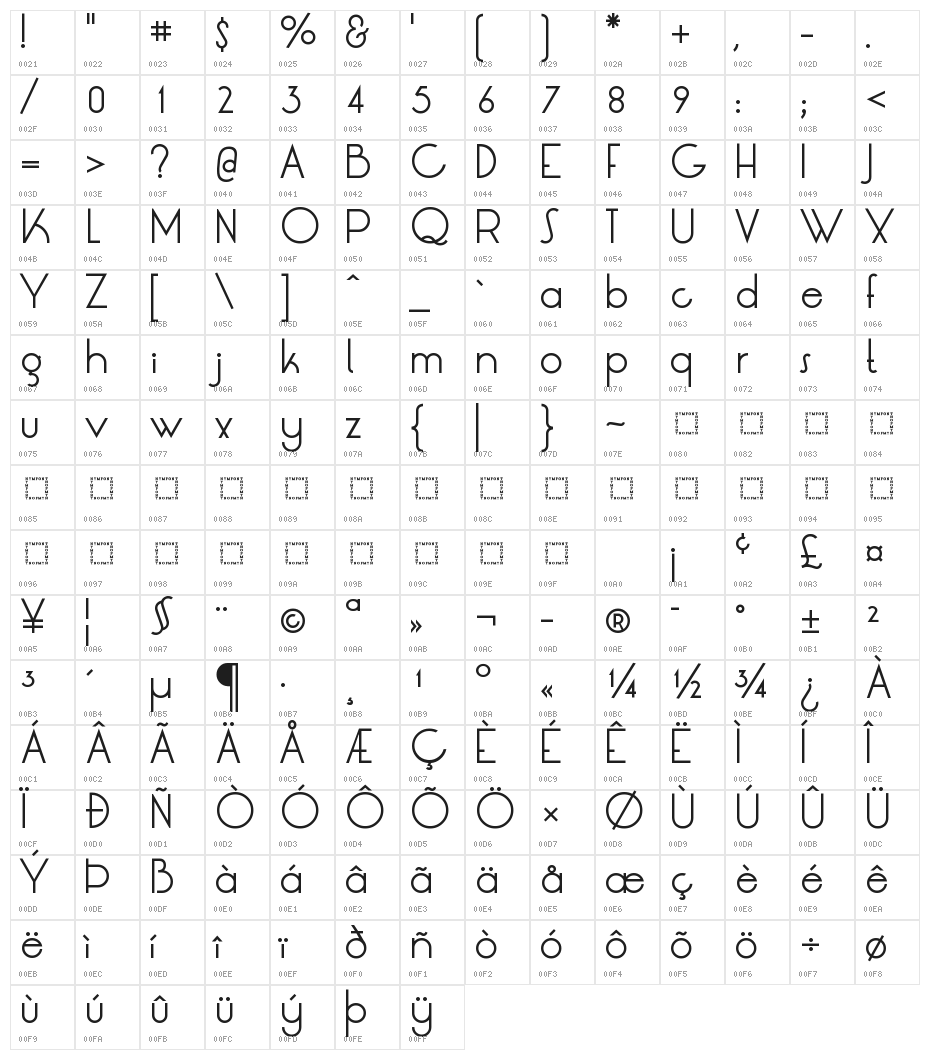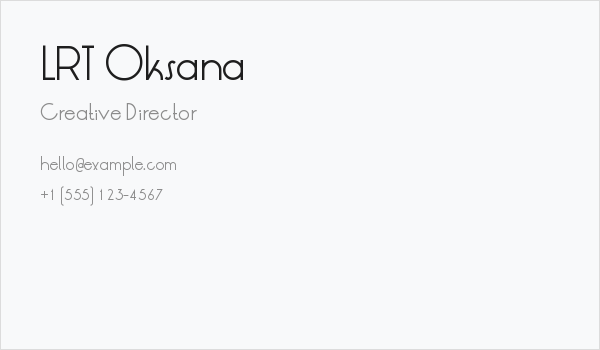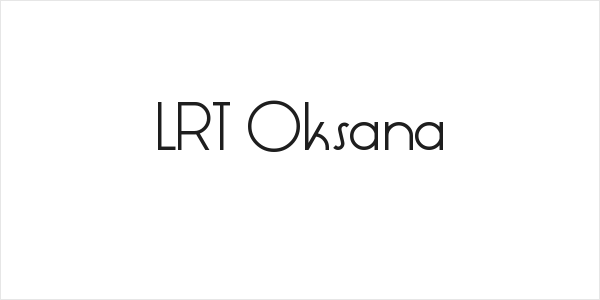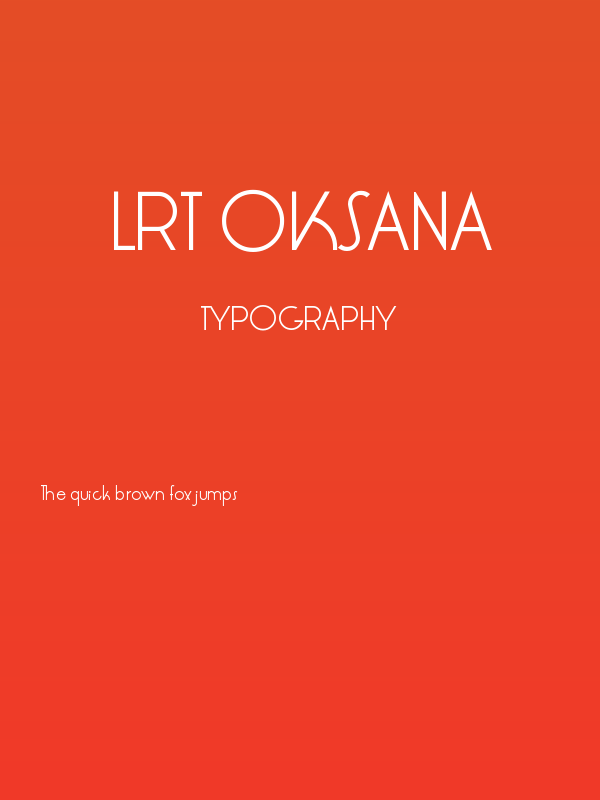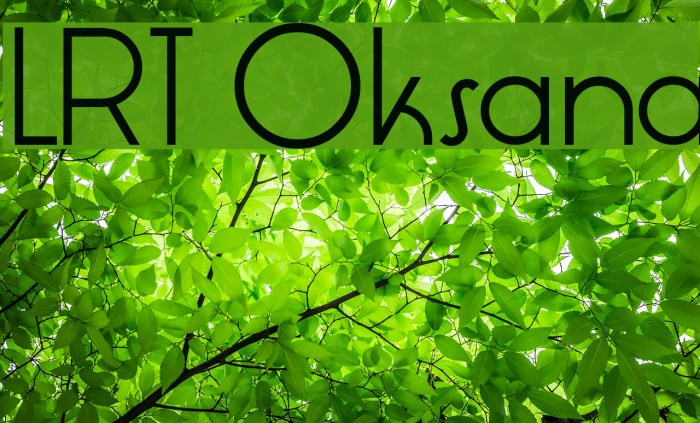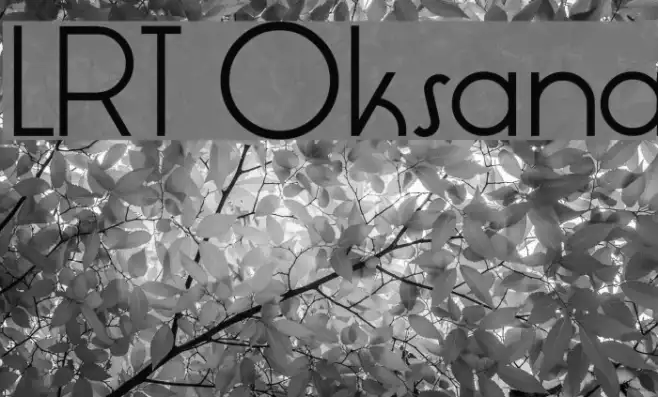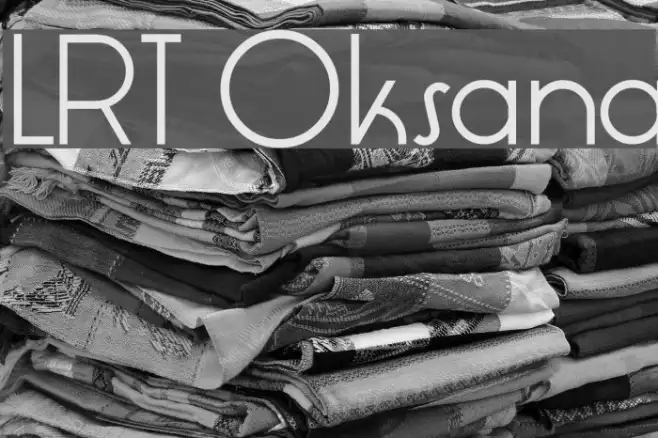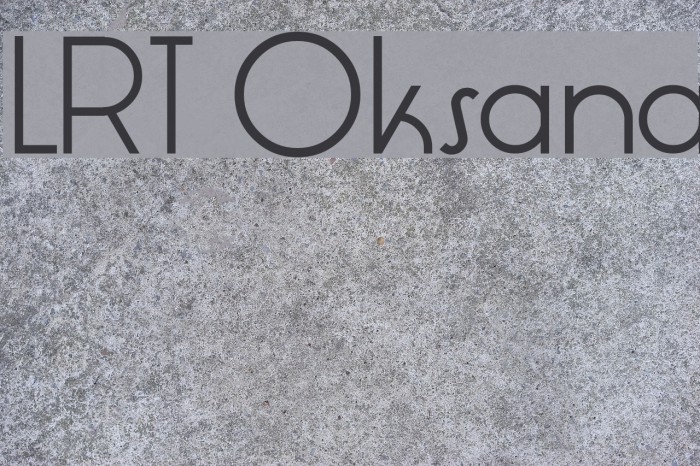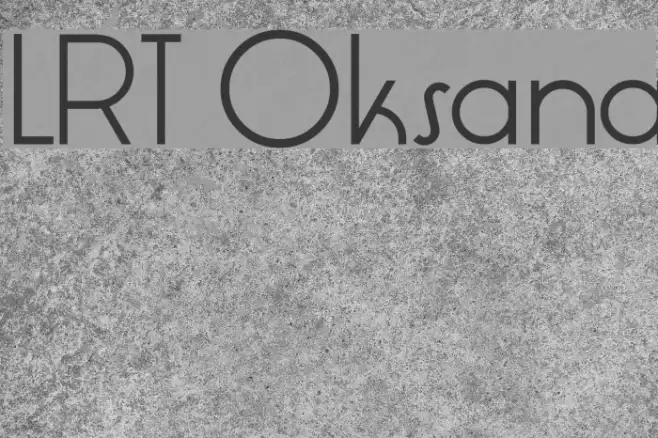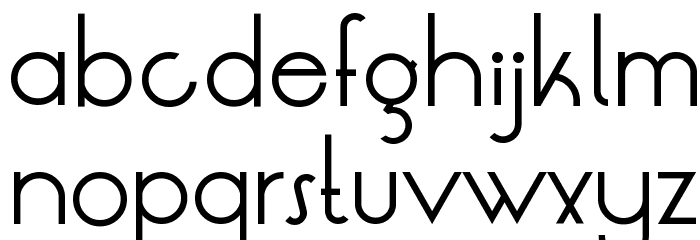
LRT Oksana Font
✎ Modern
| Anwendungsfall | Headlines, Logos, Branding |
| Vorgeschlagene Projekte | Ideal for branding, editorial design, advertising, and web design projects that require a modern and sophisticated look. |